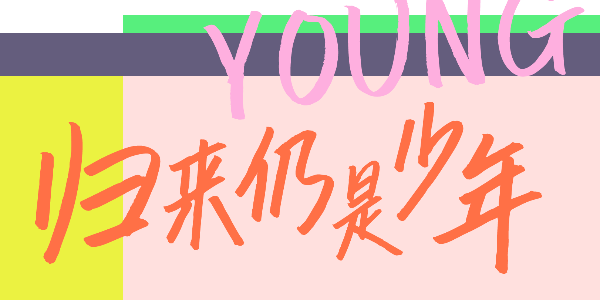
这款手写字体也太有爽感了
弹性/动感/劲直/爽朗/韧性
“汉仪艾米飞鸟体”是由汉仪签约设计师麦点盛世刘辉设计的一款手写体。设计师将这款字体作为送给女儿的礼物,并用女儿的名字艾米为这款字体命名。
设计师刘辉在研究秀丽体书法的创作实践中,设计出了这款充满弹性、韧劲和速度感的手写字体。在研习过程中,该字体已被作者运用到武汉抗疫宣传、品牌广告等多种场合之中,受到业界广泛好评。该字体简洁直爽、充满动感,适用于广告招贴、影视宣传、综艺包装等多种场合。字形打散使用,能够更能凸显这款字体的节奏感。
汉仪艾米飞鸟体|飞扬字形
“汉仪艾米飞鸟体”字形整体偏窄,横笔画均向右上方倾斜,形成群雁齐飞的排布气势,带来强烈的整齐感与节奏感。
“汉仪艾米飞鸟体”字体结构中心略向左偏,结构布局左密右舒,形成向前飞行的动感。中心的偏移也为笔画的向右舒展带来了充足的空间,形成一种类似翅膀的感觉。
汉仪艾米飞鸟体|劲直笔画
“汉仪艾米飞鸟体”对笔画做了大量的简化处理。书写时削去弯钩、笔锋平直处理、减弱起笔收笔时的顿笔感,降低撇捺笔画的弧度,使整个字形更显劲朗,简洁明快。
“汉仪艾米飞鸟体”充分运用秀丽笔的笔尖特性,在笔画转折处绘制成彩带般柔韧的姿态,使笔画转折充满动感、弹性。起承转合之间略带连笔效果,使得整个字形更显速度感。
汉仪艾米飞鸟体|中西文匹配
“汉仪艾米飞鸟体”西文部分也是由设计师亲笔绘制,字母整体向右倾斜,与中文搭配时能够呈现良好的视觉效果。
汉仪艾米飞鸟体|字体样张